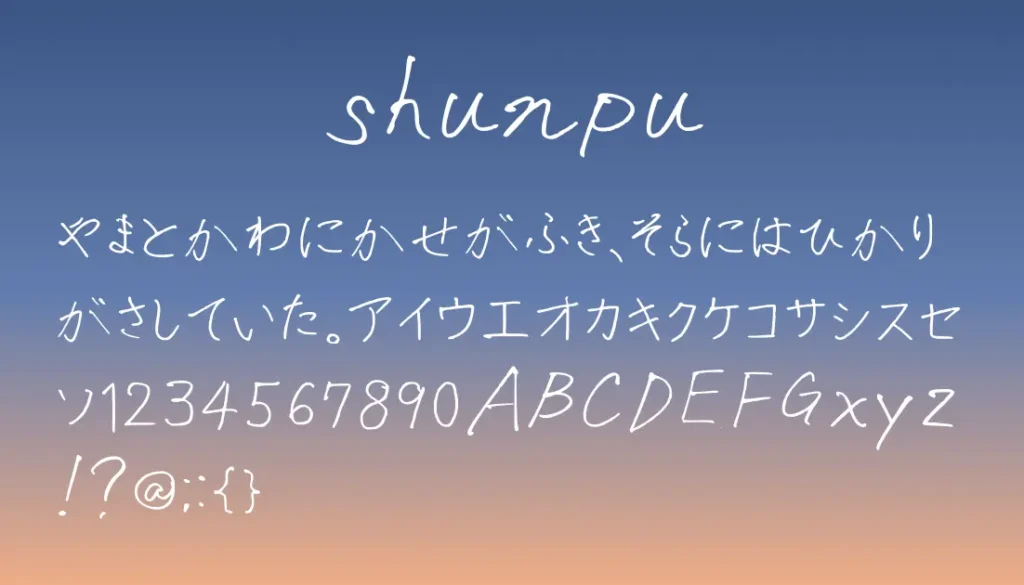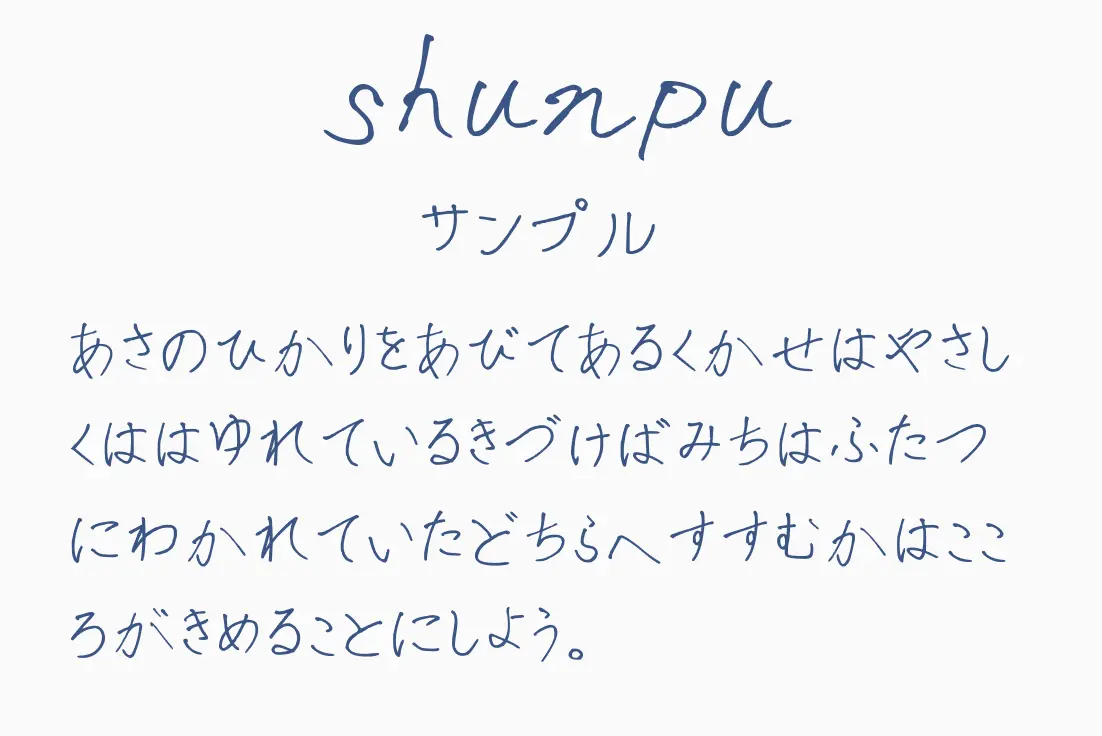
さらりと走る筆跡が心地よい、軽やかな手書きフォント。力みすぎない自然な流れと、ほどよい抜け感が魅力で、タイトルやアイキャッチに使うと一気に空気が動きます。主張しすぎないのに印象に残る絶妙なバランスで、ロゴやSNS画像、バナー制作にもぴったり。ラフさの中にセンスが光る、今っぽい雰囲気をまとった一書体です。
瞬風 shunpu